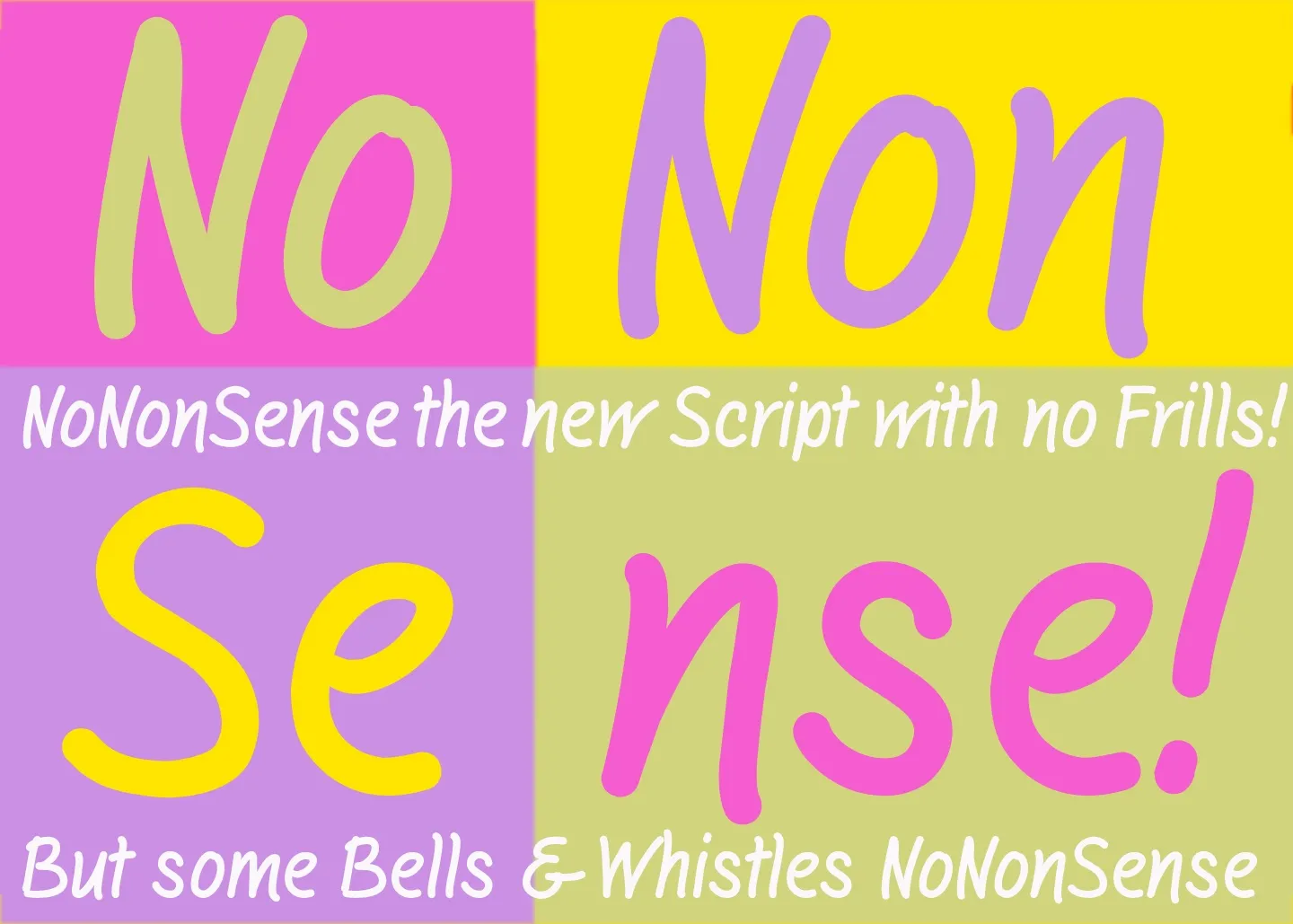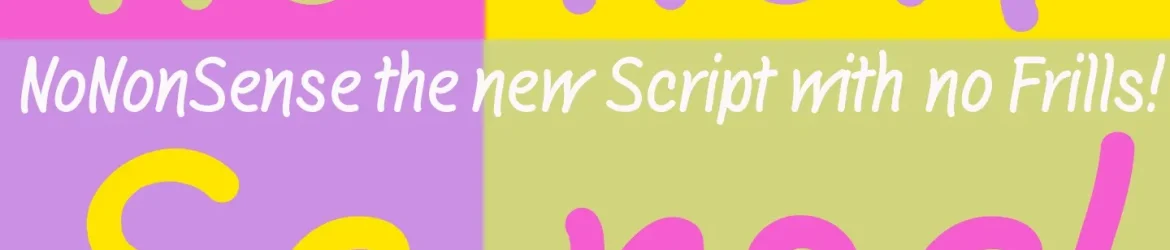
A NoNonSense Font é uma elegante escolha para quem busca simplicidade e estilo na tipografia. Desenvolvida pelo designer Hamilton, esta fonte está disponível gratuitamente, mas com um design que ressalta a simplicidade e direto ao ponto. A NoNonSense se destaca por ser uma fonte escrita à mão sem frivolidades ou adereços exagerados. Com um estilo limpo e minimalista, ela é perfeita para quem busca uma personalização original com um toque que não interfere em sua estética. A ideia de “No NonSense” está bastante clara: simplesmente escreva como você mesmo faria. É ideal para anúncios, identidades corporativas ou qualquer projeto onde deseja transmitir uma mensagem direta e confiante. Composta por um conjunto amplo de caracteres, a NoNonSense é perfeita para designers que buscam uma fonte escrita à mão sem se preocupar com detalhes excessivos. O resultado é uma escolha conveniente para qualquer designer, desde iniciantes até profissionais experientes. A fonte é uma ótima opção para aqueles procurando um design minimalista e agradável aos olhos, oferecendo a liberdade de expressar-se de maneira autêntica em seus projetos.